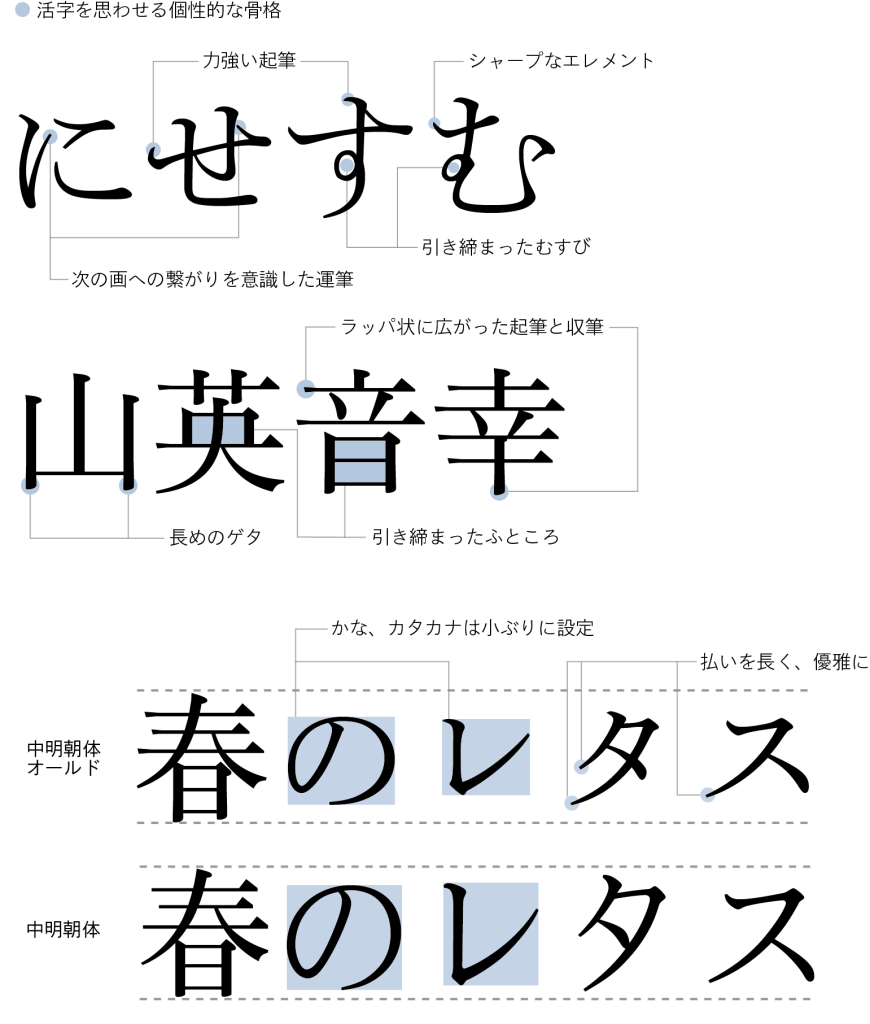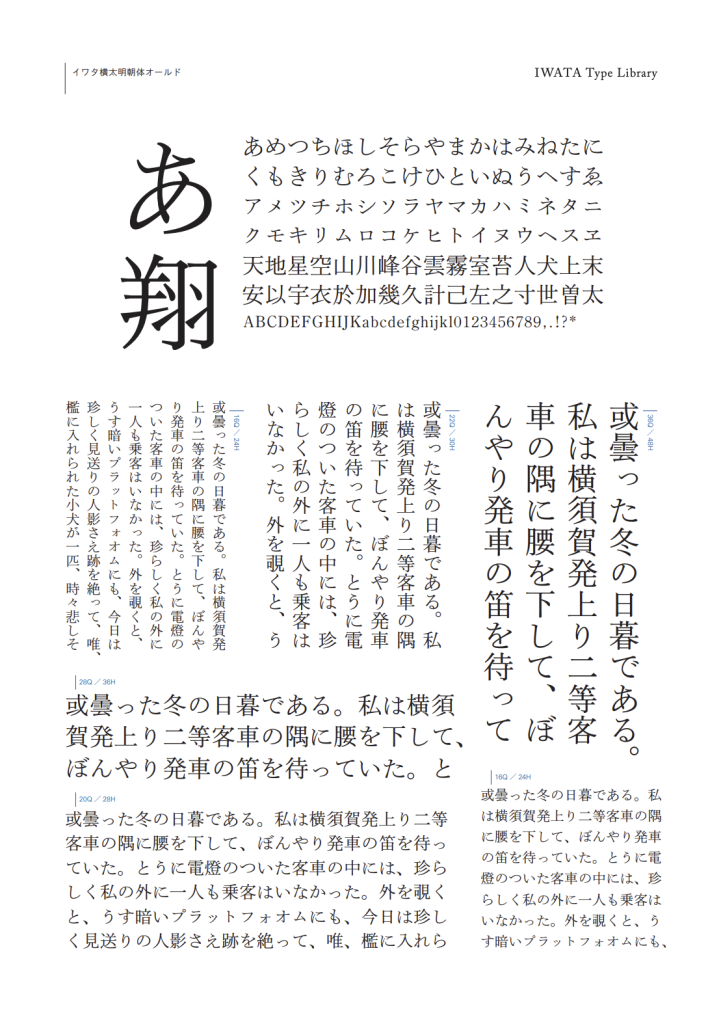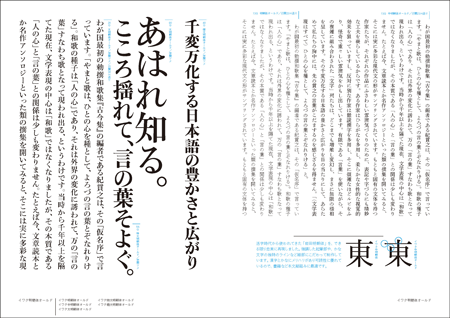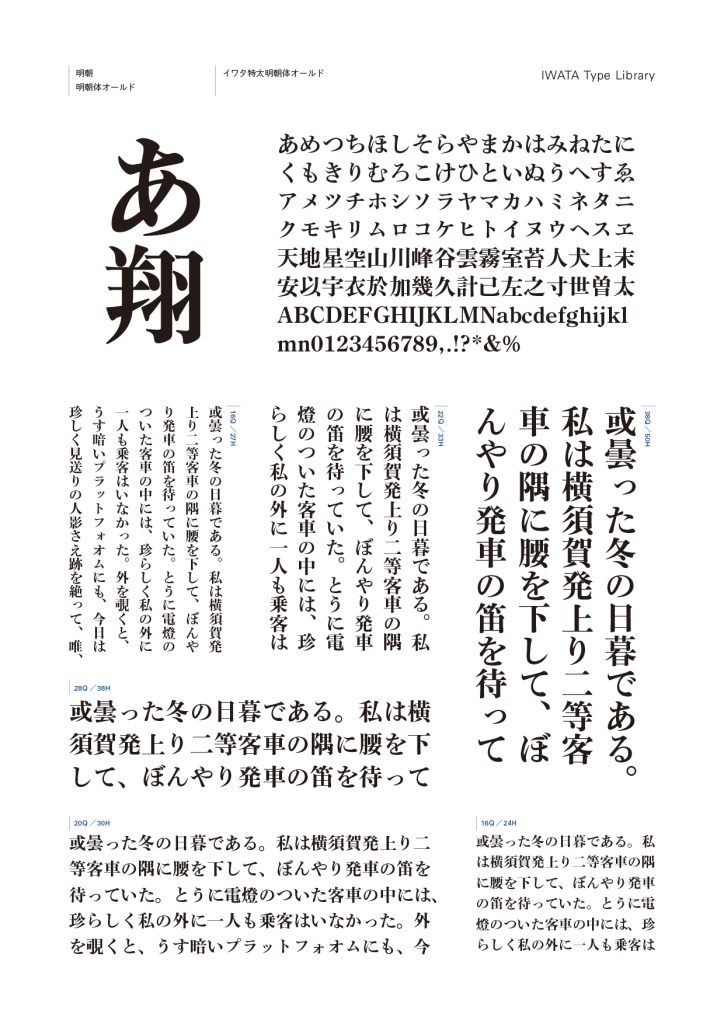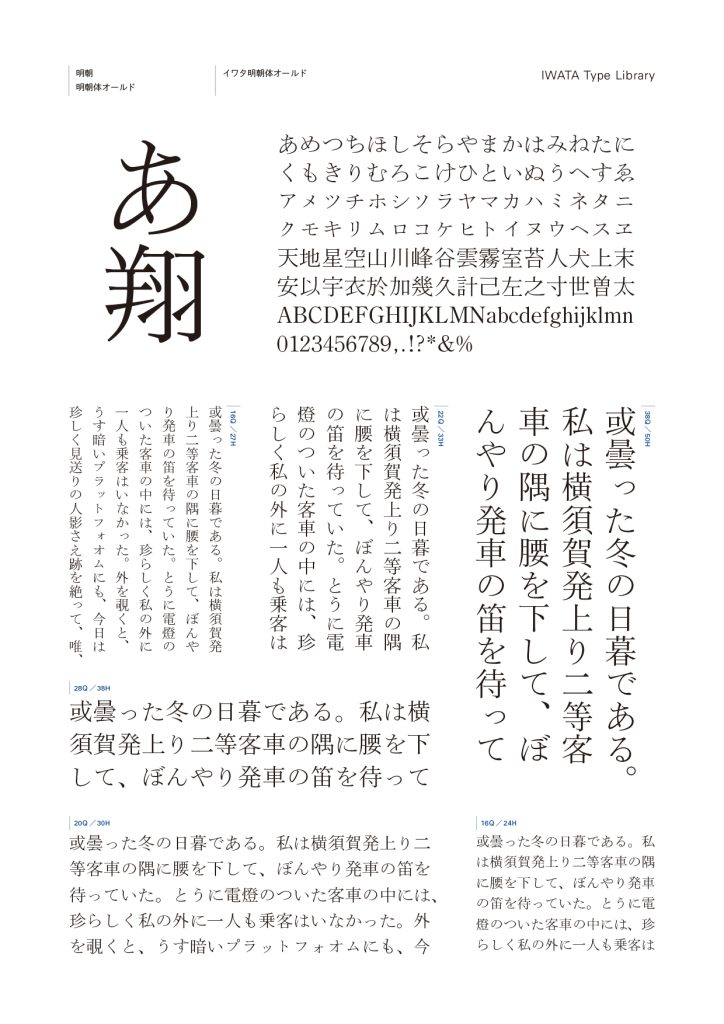
金属活字の時代から多くの人に愛されてきた「岩田明朝体」の美しさと力強さ、可読性の高さを再現したオールドスタイルの明朝体です。活字時代の特徴を尊重し色濃く残しながらも可読性を向上させる工夫を施した、現代のデザイン環境にも適応する書体です。また、「イワタ明朝体オールド」を電子媒体での表示環境によりフィットさせるために調整した「イワタ横太明朝体オールド」を追加しています。
書体デザインのポイント
活字の持つシャープなエレメントと引き締まったふところが特徴です。ラッパ状に広がった起筆・収筆部をもつ漢字や、仮名の形状は金属活字の特徴を受け継いでいます。
イワタ横太明朝体オールドはイワタ明朝体オールドをさらに使いやすくすることをテーマに、横画を中心に全体を少し太く調整しています。これにより、印刷はもちろん電子媒体でのちらつきや光源による文字痩せにも強い、快適に読める設計となっています。